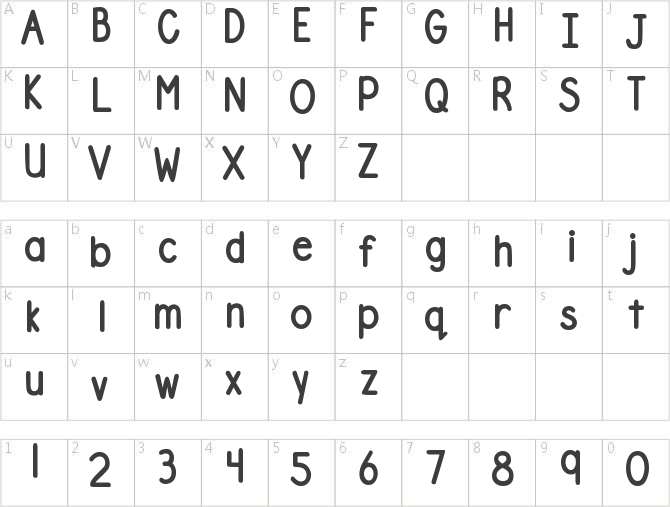
DJB Number 2 Pencil Bold
DJB Number 2 Pencil Bold介紹
DJB Number 2 Pencil Bold字體字庫(kù)是一款讓人賞心悅目、百看不厭的英文字體,適合各類廣告和產(chǎn)品包裝設(shè)計(jì)應(yīng)用,字體大小0.04MB,格式為ttf字體,上傳用戶是小北,作者/版權(quán)方為未知